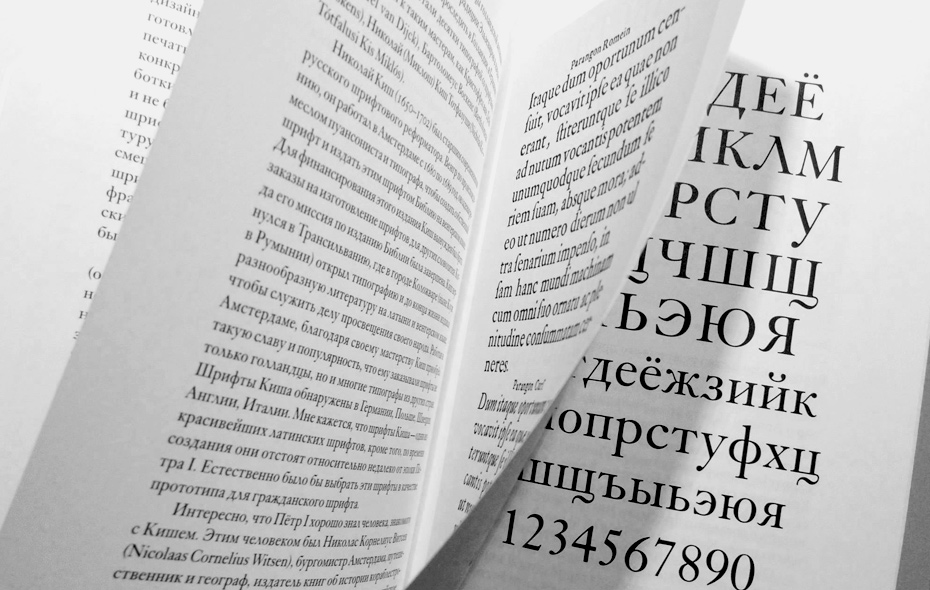
Письмо читателям
(с картинками)
Дорогие читатели! Можно сказать, что первый этап турбулентности, связанный с запуском журнала, позади: на настройку сайта и редакционной жизни ушло около пяти месяцев. Теперь мы можем поговорить о планах и публикациях, которые будут появляться на страницах «Шрифта» в обозримом будущем. В этом письме я начал было охать, что мы задерживали выход материалов, создавали вам неудобства в доступе к архиву (долгое время его просто не было), но ещё раз посмотрел на сделанное и запланированное и выпрямил спину: главное произошло — у нас есть журнал, а у вас есть возможность его читать.
Евгений Юкечев
ожалуй, лучшее, что можно предпринять в начале отношений — поделиться своими планами. Руководствуясь этим благим побуждением, мы приготовили для вас обзор публикаций и наших задач на ближайший год.
Тематический план
Прежде всего, мы хотим представить вам страницу содержания журнала, где размещены все вышедшие тексты и опубликован тематический план с синопсисом материалов на ближайшие месяцы. Ссылка на содержание теперь всегда будет находиться в верхней части сайта. Можно считать этот план и манифестом, и декларацией нашего журнала, поскольку в нём несложно разглядеть основные ориентиры. Это не означает, что, кроме запланированного, ничего не будет появляться, но то, что указано в предварительном графике, выйдет точно. Опыт подготовки предыдущих публикаций показал, что редакции при её нынешней ловкости по силам выпускать два материала в месяц. Простой арифметический подсчёт даёт прогноз на двадцать четыре темы в год, тогда как в работе у нас уже значатся около сорока текстов. Надеемся, у нас хватит сил план перевыполнять.
Исторические исследования
Продолжаем готовить статьи о русских типографах, дизайнерах, художниках шрифта, специалистах и людях профессии. «Фаворский? Проходили», — отвечает выпускник графического отделения. Благодаря архаичным учебным программам Фаворский стал «пройденным материалом», а не той вершиной, о которой в 1923 году писал искусствовед Абрам Эфрос: «Единственная точка, где мы стоим выше европейского искусства, — это наша гравюра на дереве». Скоро выйдет в свет цикл о Владимире Фаворском: Юрий Герчук рассказал о времени и событиях, повлиявших на судьбу художника, а текст шестой главы «О шрифте» прояснит ситуацию с «буквами и мухами в молоке».
Фрагмент иллюстрации к главе VI. «О шрифте» очерка «О графике как об основе книжного искусства»
(М.: Искусство книги, 1976)
Несколько очерков в плане посвящено событиям и людям 30-х годов. Константин Головченко подготовил подробный материал о введении в 1930 году Общесоюзного стандарта 1337 «Шрифты гартовые», который касался ручных шрифтов и определял, какие из них годны для советской печати, а какие следует переплавить. Очевидно, что результаты этих инициатив отразились на нашей типографической истории плачевным образом (как и вся тьма последующих событий).
«Ренегат!» — врывается в помещение раскрасневшийся Соломон Телингатер после выступления Яна Чихольда на международной выставке искусства книги, проходившей в Лейпциге в 1964 году. Мы начали работать с архивом Соломона Бенедиктовича. В доме сына Телингатера на книжном шкафу хранится несколько внушительных, аккуратно подписанных и туго обвязанных папок. В архиве собрано большое количество работ отца, в том числе и фронтовых. Эскизы титульных листов, многочисленные варианты конструктивистских обложек, буквицы, алфавиты и публикации — это целые дни сканирования для подготовки электронного архива. Открытием для нас стал разработанный Телингатером «единый алфавит для различных языков, возникших на латинской и греко-кириллической основе», — эксперимент уникальный, в своё время вызвавший интерес международного типографического сообщества. Запись на русском языке в его представлении могла бы выглядеть так:
Иллюстрация набора текста на русском языке с использованием унифицированного алфавита. Текст опубликован впервые на немецком языке в издании Papier und Druck. Лейпциг, 1968
Библиотека журнала «Шрифт»
В прошлом году дебютировала серия «Библиотека журнала „Шрифт“»: мы выпустили очерк Владимира Ефимова «Гражданский шрифт и кириллический Киш». На этот год запланировано ещё два издания по следам циклов публикаций: «Шрифт в творчестве Владимира Фаворского» и «Шрифтовое наследие Соломона Телингатера». Каждую из этих брошюр мы бы хотели издать и на английском языке, но пока оставим эту мысль на полях. Через некоторое время придумаем, как распространять наши издания, и сообщим дополнительно. А если у вас появятся вопросы, вы сможете задать их редакции по адресу: welcome@typejournal.ru
Брошюра «Гражданский шрифт и кириллический Киш», Владимир Ефимов (М., Серия «Библиотека журнала „Шрифт“», выпуск I, 2013). Фото — Яна Кутьина
Can you read Cyrillic?
Обзор шрифтов за 2013 год ещё раз проявил положение в лагере «иностранной» кириллицы. Характерно, что среди выбранных редколлегией журнала десяти лучших шрифтов прошлого года все авторы кириллицы — русскоязычные дизайнеры. Этому есть объективные причины: информации об истории, специфике и удачных примерах кириллических шрифтов, доступной западным дизайнерам, драматически мало, а для самостоятельного изучения особенностей кириллицы нужны весомые аргументы и искренний интерес. Или хотя бы потенциал рынка. Какие шансы в сложившихся условиях дизайнеру, не владеющему русским языком, получить убедительный результат? За грубым образом кирилловского забора и «стремительной эволюцией» наших шрифтовых форм дизайнерам сложно разглядеть те «нежные места» и исторические предпосылки, от которых зависит точный — а порой, и просто корректный — образ. Возможно, запуск английской версии журнала с переводом ключевых материалов о проектировании и истории кириллицы сможет стать поводом к изменению печальных тенденций.
Руководитель магистерской программы дизайна шрифта Университета Рединга (MA Typeface Design, University of Reading) Джерри Леонидас вместе со студентами рассматривает сайт журнала «Шрифт», который они пока не могут прочесть. Рединг, декабрь, 2013 год. Фото — Евгения Басырова
Шрифт и типографика сегодня
В редакции появилась пятнадцатичасовая запись беседы Максима Жукова с Мишей Белецким. Пока мы в некоторой растерянности относительно формата публикации, но после расшифровки появится больше ясности. Михаил Аникст любезно согласился принять у себя в гостях в Лондоне журналиста Юлию Богатко и рассказал о разработке графической системы для Олимпийских игр 1980 года в Москве. В свеженаступившем году нас также ждёт ряд содержательных интервью: Джерри Леонидас (Gerry Leonidas), Пола Шер и Майкл Берут (Paula Scher, Michael Bierut), Самнер Стоун (Sumner Stone), Дэн Рэтиган (Dan Rhatigan), Герард Унгер (Gerard Unger), Тагир Сафаев, Гаянэ Багдасарян и Маша Дореули поделятся с читателем мыслями, опытом и своим бодрым расположением духа. А Владимир Кричевский в свойственной ему горячей манере нанесёт ультимативный удар «шрифтоцентризму» в своём манифесте: «Шрифтовики не должны плодиться как грибы. Новые гарнитуры не должны печься как блины. Даёшь прекрасные шрифты, но пореже и поосновательней! Даёшь русский „тайп-дизайн“ — во благо хороших зрительных форм добродетельных текстов!»